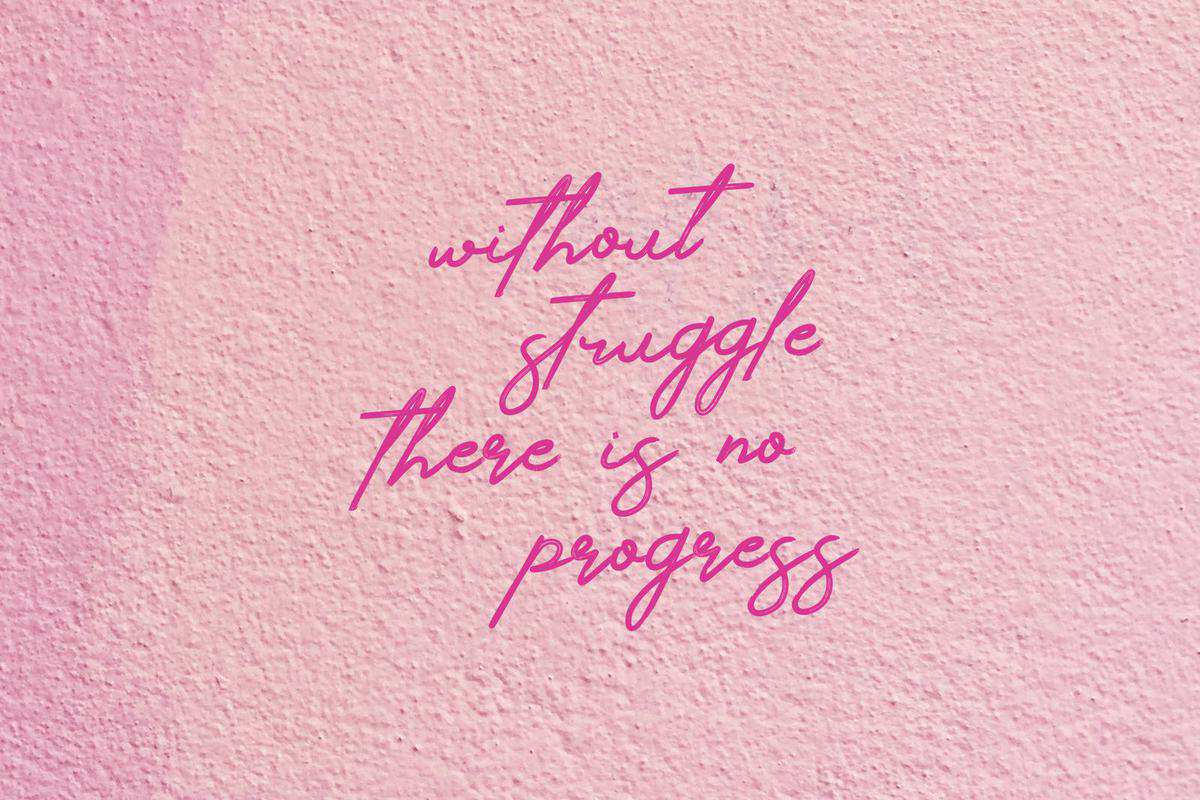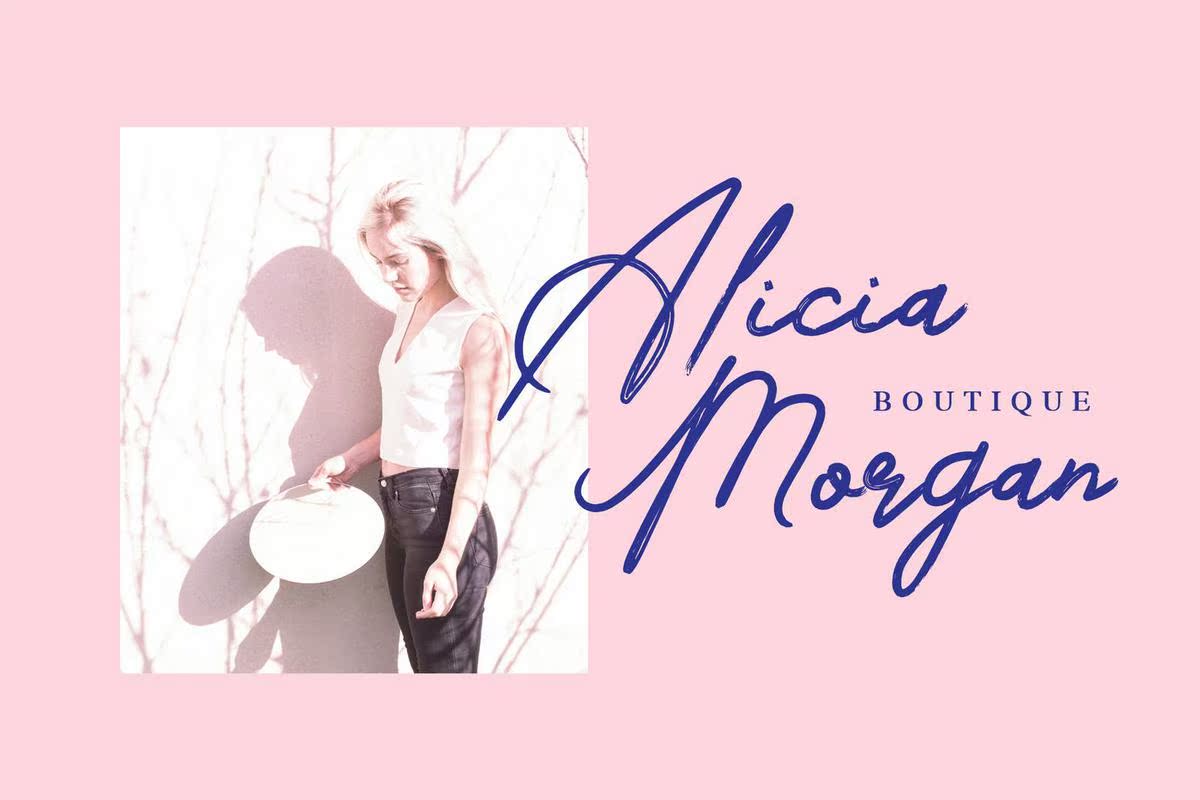
Olivient是一种手写字体,字体粗体、粗壮、自然。Olivient字体具有自然的特点,适用于徽标、社交媒体、广告、产品包装、产品设计、标签、照片、水印、邀请、,文具商和其他任何需要使用简洁样式字体的项目,或将简洁文本覆盖在任何背景图像或QuoteImages上。Olivient是手写字体字体,字体粗体、粗壮、自然。Olivient字体具有自然特征,适用于徽标、社交媒体、广告、产品包装、产品设计、标签、照片、水印、,邀请函、文具商和其他任何需要AbrushStyleFontor的项目,或者在任何背景图像或QuoteImages上显示简单的文本。